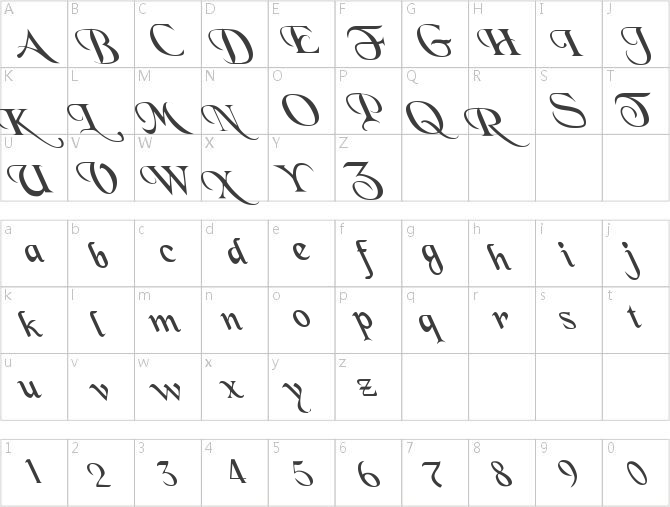
Black Chancery Extreme Lefty
Black Chancery Extreme Lefty介绍
Black Chancery Extreme Lefty字体字库是一款让人赏心悦目、百看不厌的英文字体,适合各类广告和产品包装设计应用,字体大小0.04MB,格式为ttf字体,上传用户是Who am I?,作者/版权方为未知